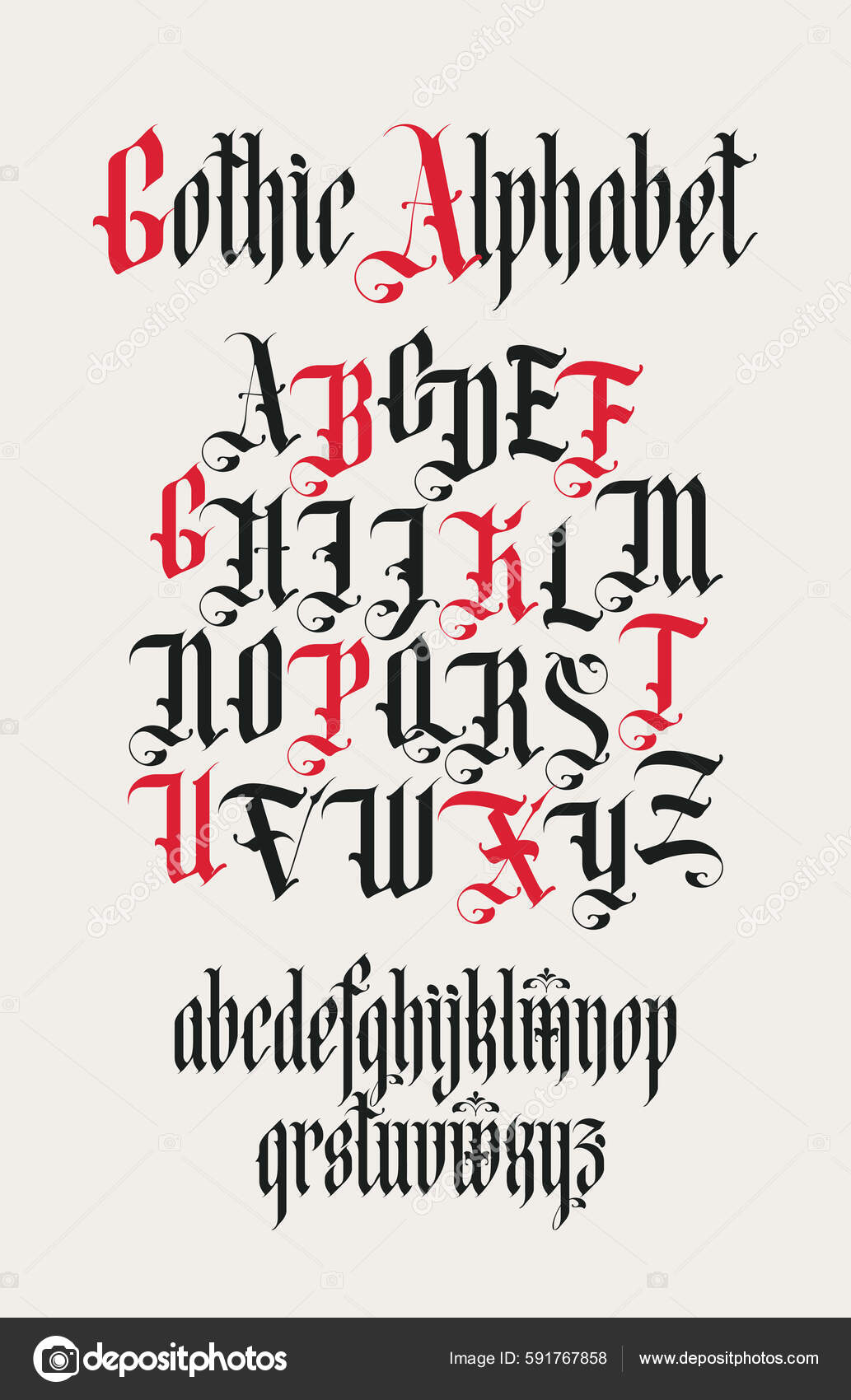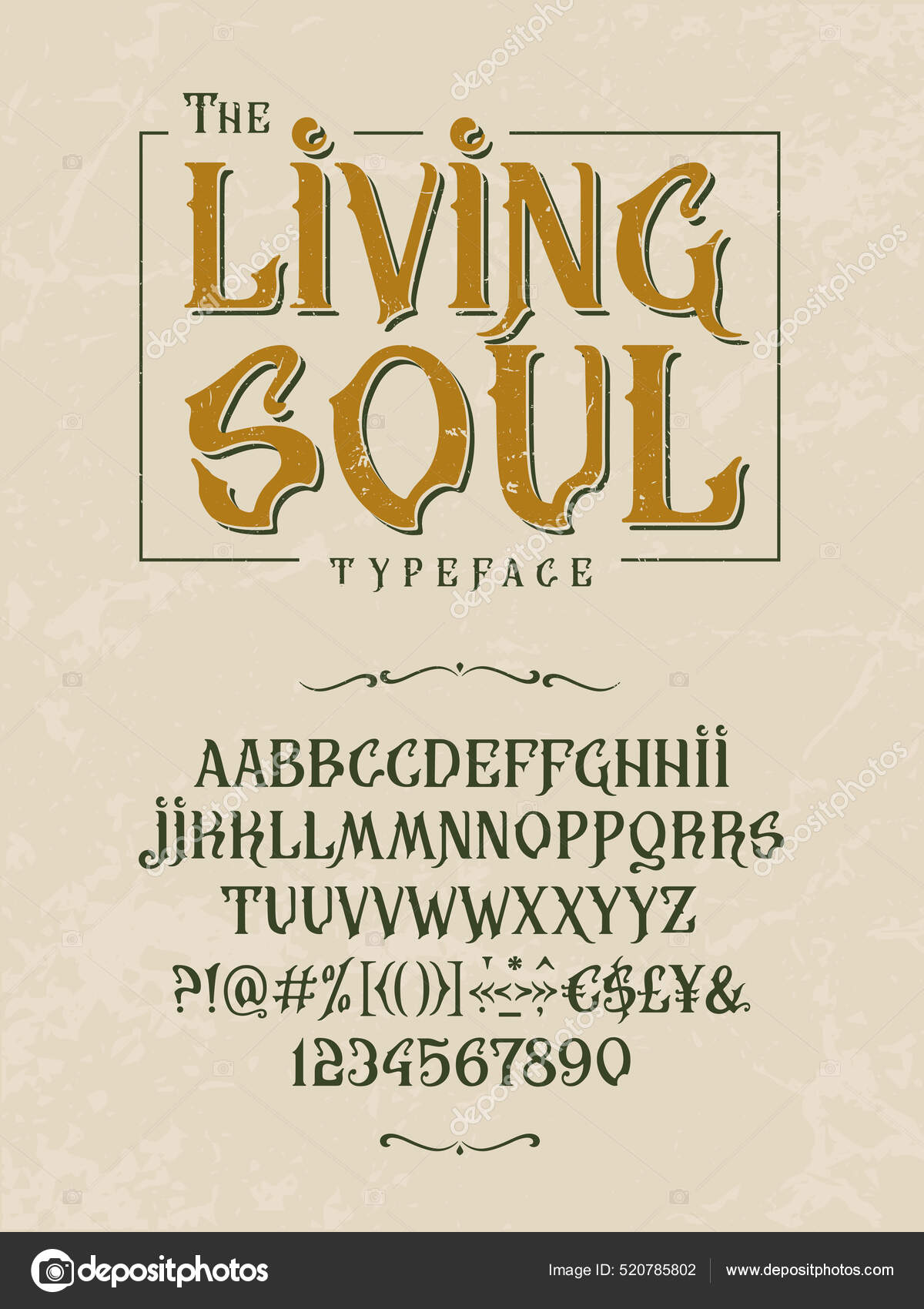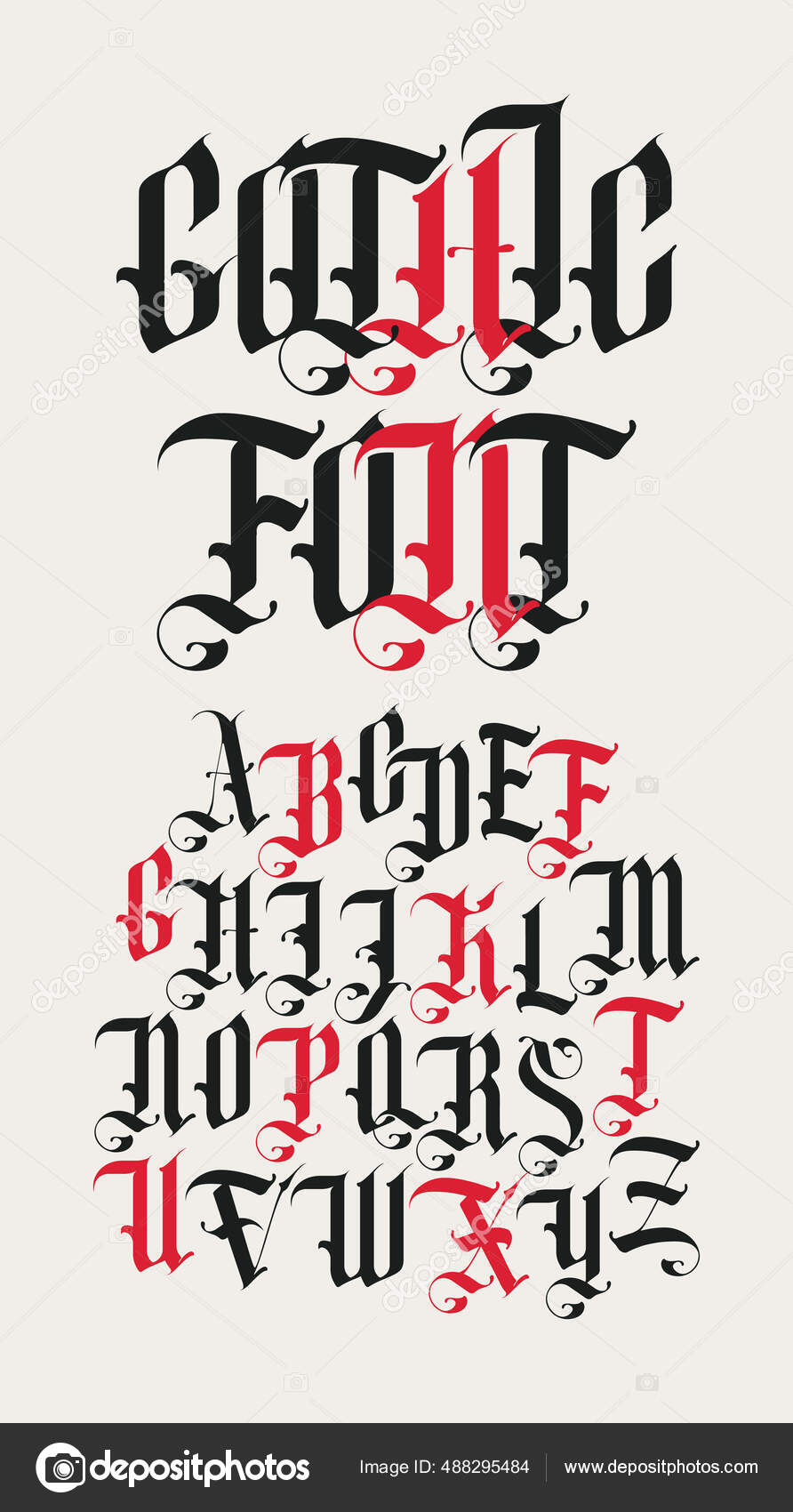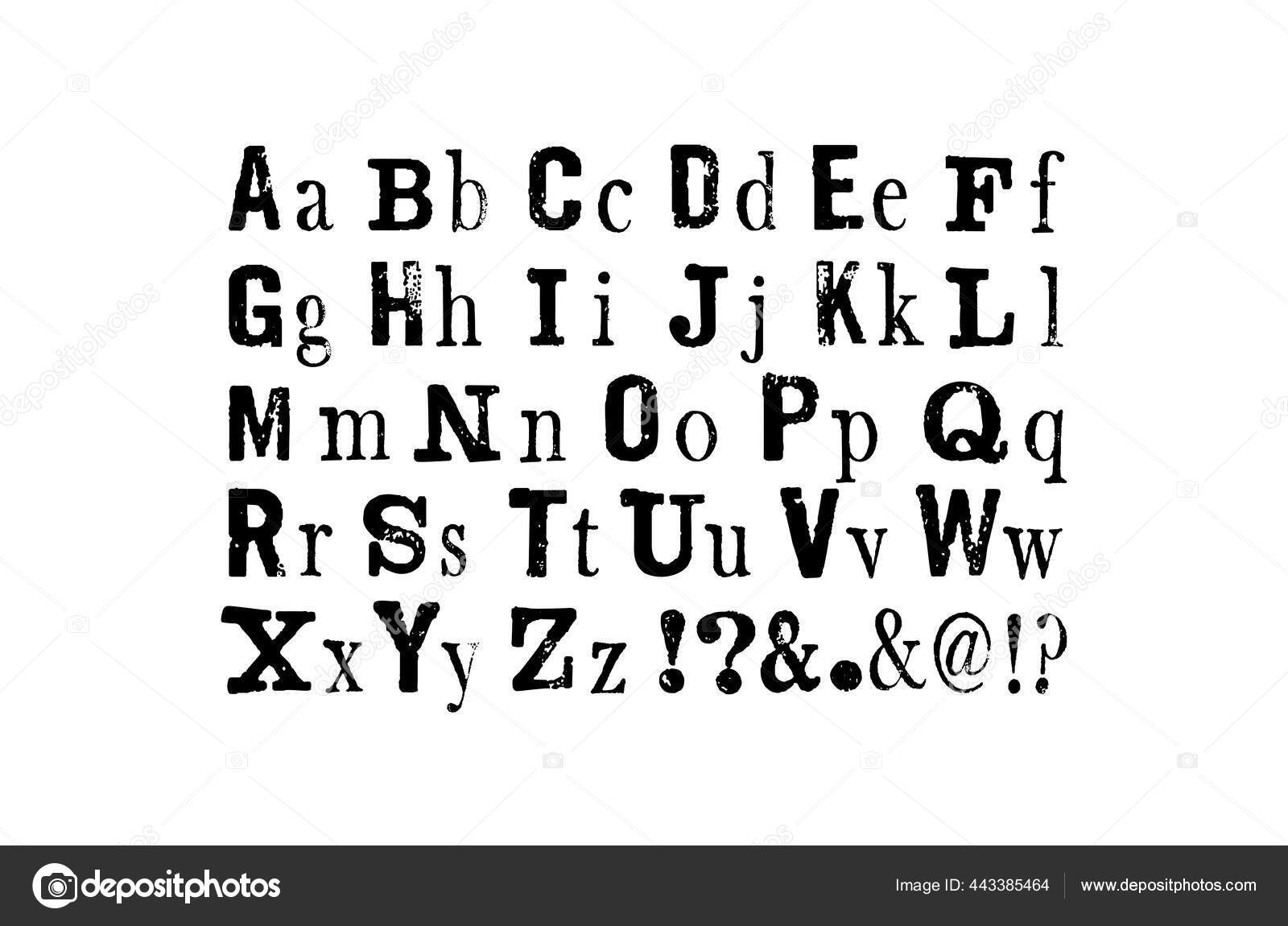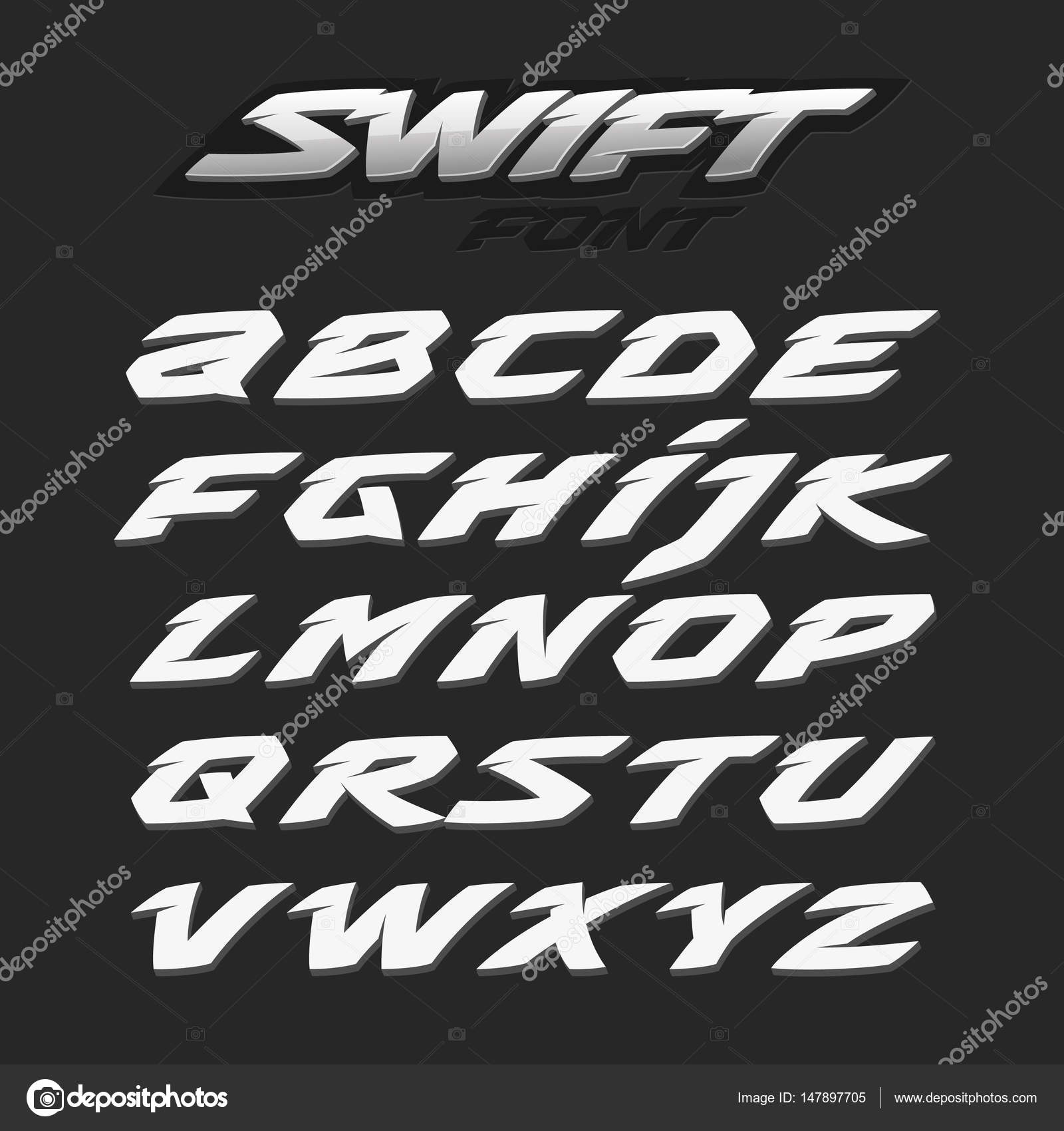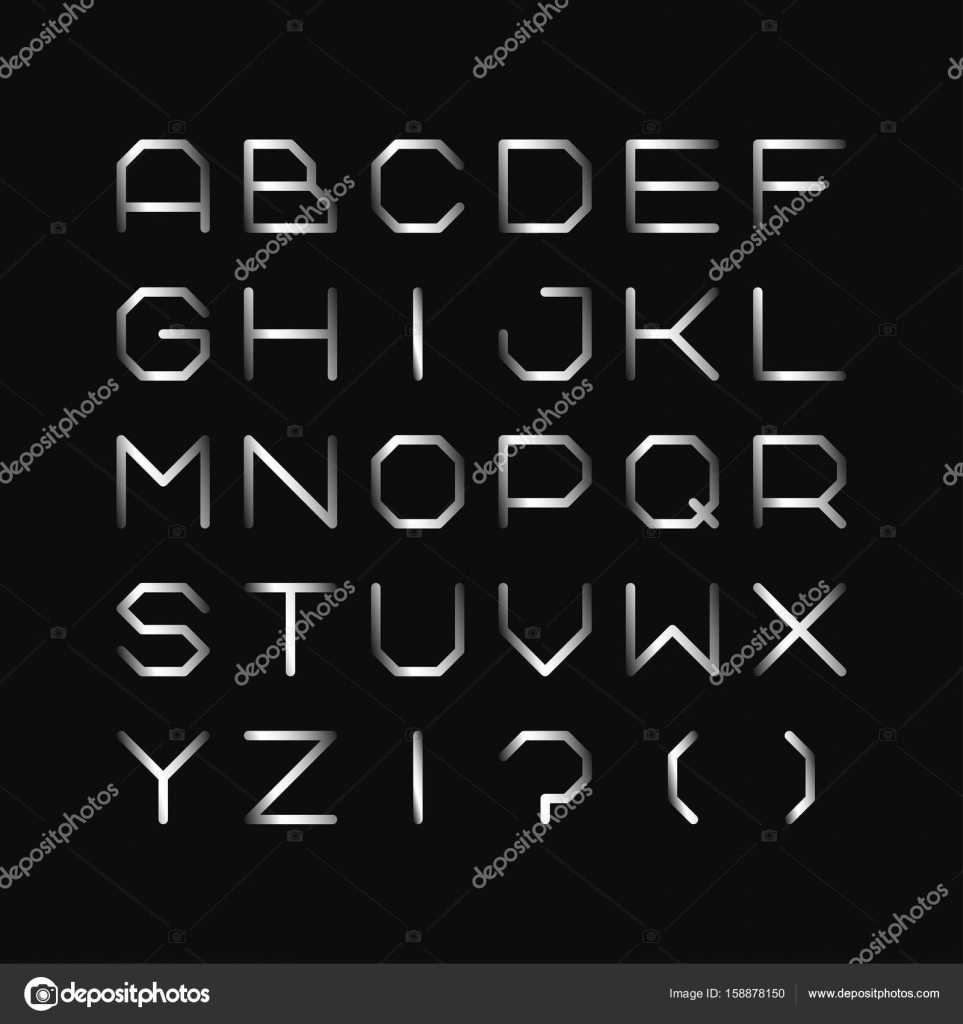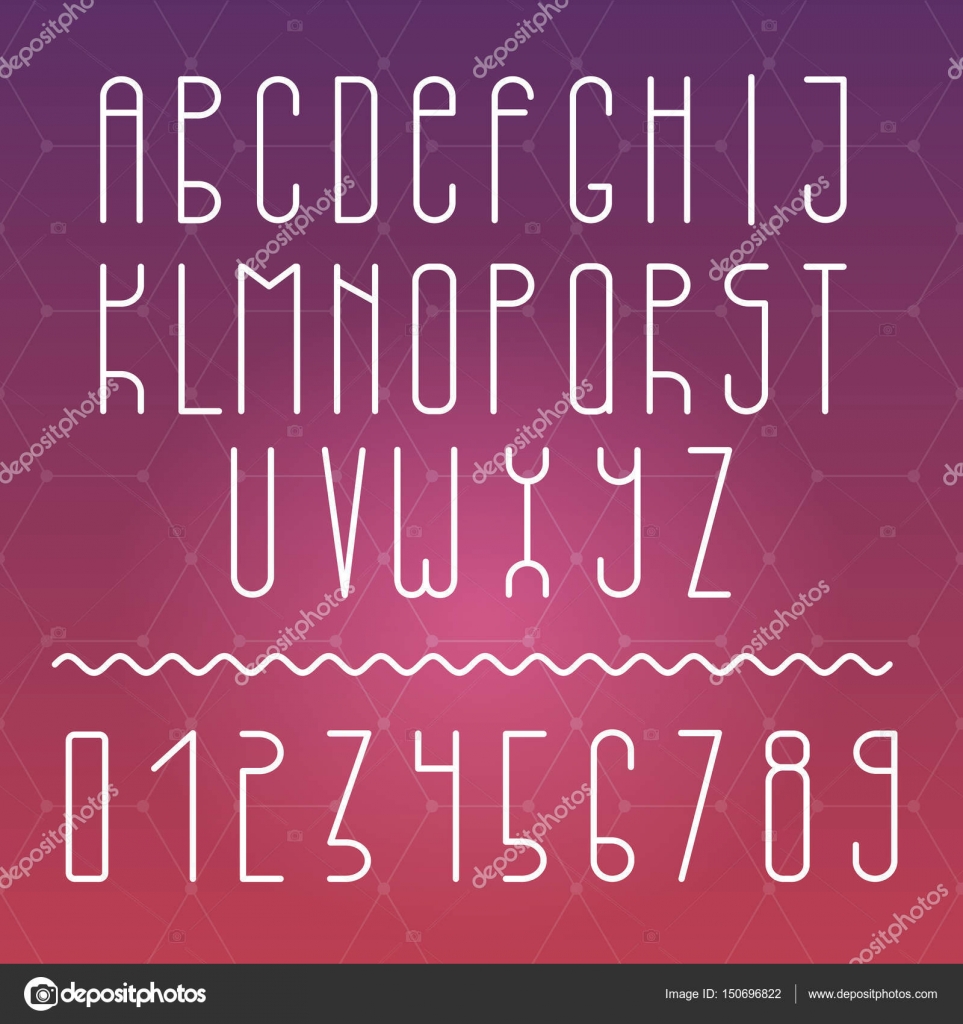
Шрифты латинские
Векторный Латинский Шрифт. Векторная Марка Abc С Граненой.
Готический Английский Алфавит Вектор Средневековые Латинские Буквы.
Векторный Минималистический Шрифт - Творческий Английский Алфавит.
В этом разделе представлены латинские шрифты. Латиница появилась в середине первого тысячелетия до н. э. и основывалась на греческом алфавите.
Шрифт Живая Душа. Винтажный Дизайн. Латинские Знаки Векторное.
Готический Шрифт Полный Набор Букв Английского Алфавита Винтажном.
Золотые Буквы Черном Фоне Современный Золотой Шрифт Латинские.
Для Западной Европы, Центральной и Юго-Восточной Европы: латинские глифы для африкаанс, албанский, баскский, боснийский, каталанский, датский, голландский.
Металлический Шрифт. Железный Английский Алфавит. Латинские Буквы.
Простой Современный Шрифт. Минималистический Английский Алфавит.
Шрифт Стиле Мозаики Латинские Буквы Цифры Камней Тротуаре.
Элегантный Шрифт Векторное Изображение ©vera.Holera 234946136
Векторная Технология Творческий Шрифт. Модный Английский Алфавит.
Готический Шрифт Полный Набор Букв Английского Алфавита Винтажном.
Векторный Дизайнер Современный Шрифт - Минималистичный Креативный.
Модный Неоновый Шрифт Современный Алфавит Двух Цветных Линий.
Кириллица Латинский Алфавит Письмо Прописные Русские Украинские.
Быстрое Футуристическое Написание Алфавита. Векторный.
Устанавливаются следующие виды шрифтов и знаков: ПО — шрифт прописной основной (русский, латинский, греческий и цифры арабские.
Готический Шрифт Полный Набор Букв Английского Алфавита Винтажном.
Каталог лучших бесплатных русских шрифтов с поддержкой кириллицы для использования в ваших проектах в Photoshop, Figma, Word и прочих;
Готический Шрифт Полный Набор Заглавных Букв Английского Алфавита.
Векторный Шрифт. Латинские Буквы И Цифры Векторное Изображение.